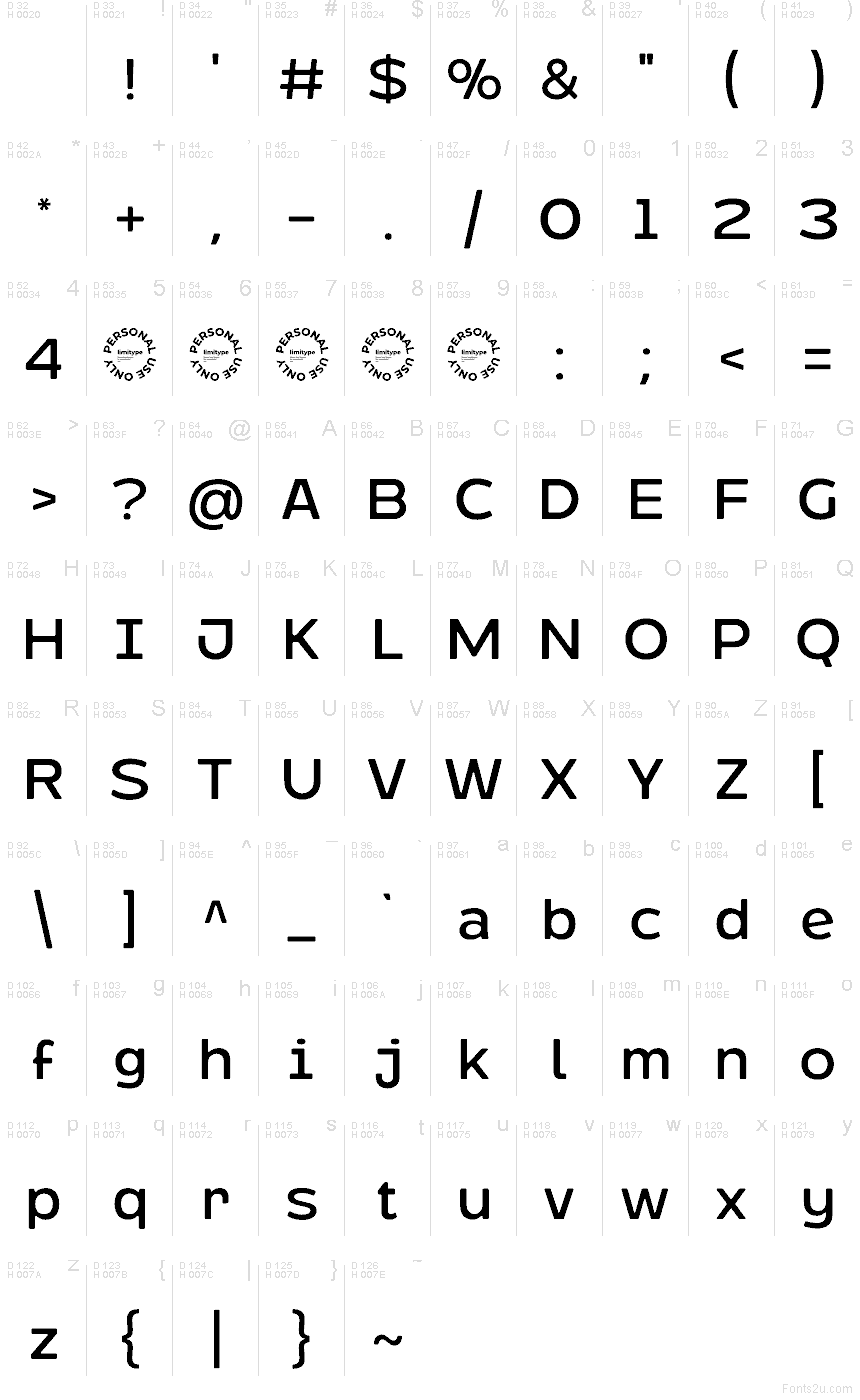
Molia Demo
Limitypeによる書体 Molia は、力強い存在感とやわらかく親しみやすい印象を絶妙なバランスで両立した、無料の丸みあるサンセリフ体です。太めのストローク、なめらかな角の処理、安定感のある縦のラインによって、文字組みにしっかりとした重みと自信が生まれます。それでいて見た目はやさしく、読みやすさも損ないません。目を引くのに、押しつけがましくならないのが Molia の魅力です。字間もゆったり設計されているので、短い単語から長めのネーミングまで、ひと目で把握しやすく仕上がります。
この無料フォント Molia は、ロゴ、アプリUI、商品パッケージ、インパクトのある見出し、ポスター、SNSグラフィックなど、あたたかさと明快さをひとつのトーンで表現したい場面で特に映えます。しっかりした字形は大きめサイズでも美しく映え、丸みのあるエッジがブランドメッセージにきつさを出しすぎません。本文用には、軽めでニュートラルなグロテスク体と組み合わせるのがおすすめです。クリーンな情報設計を保ちながら、人の温度を感じるタイポグラフィに仕上がります。